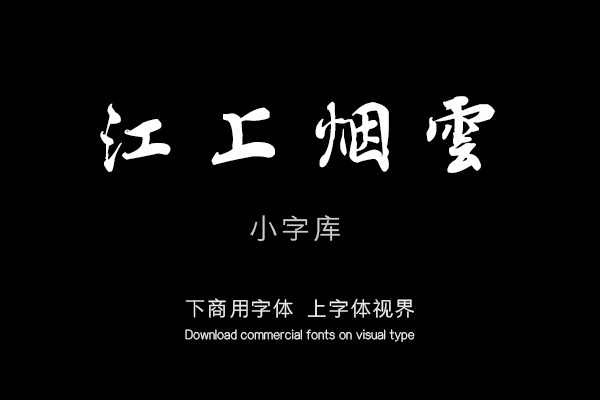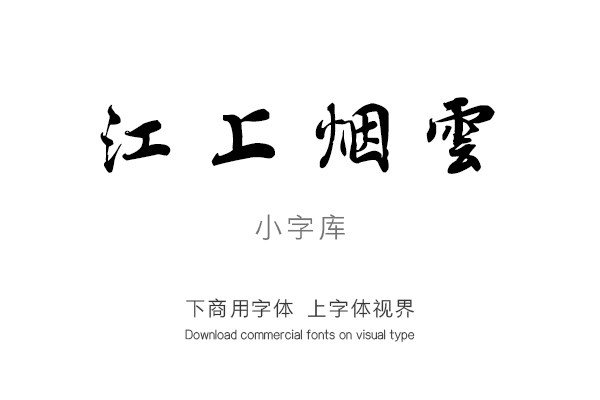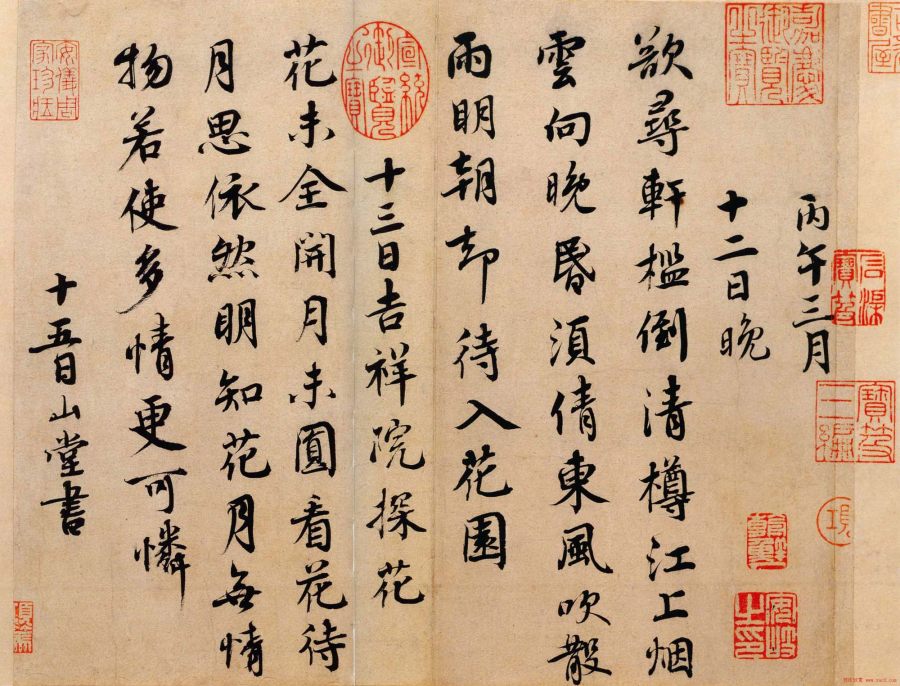
汉标蔡襄山堂诗帖
94个字。蔡襄书法欣赏《山堂诗帖》高清晰图片 1066 纸本 24.8cm X26.7 cm 台北故宫博物院藏.
《丙午三月十二日晚》“欲寻轩槛倒清樽,江上烟云向晚昏。须倩东风吹散雨,明朝却待入花园。”《十三日吉祥院探花》“花未全开月未圆,看花待月思依然。明知花月无情物,若使多情更可怜。”十五日山堂书